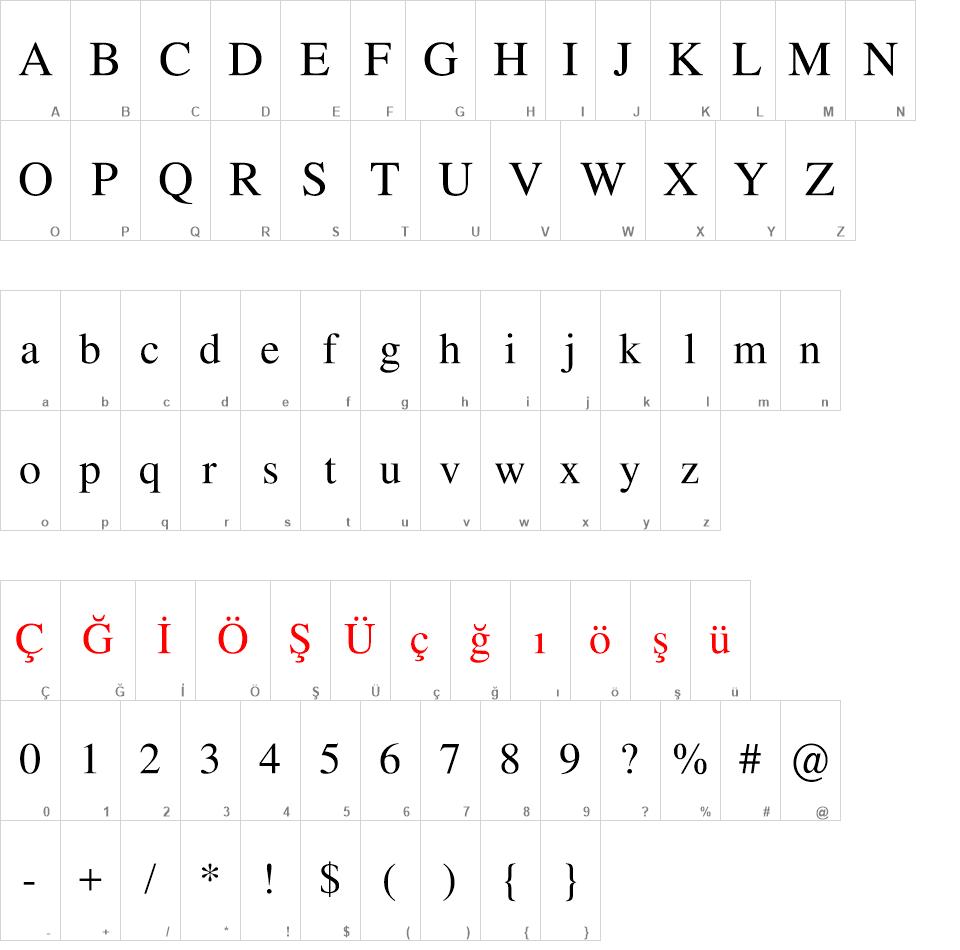
Nimbus Roman No9 L Font Family
Aus Wikipedia: Nimbus Roman ist eine Serifenschrift, die 1982 von URW Studio erstellt wurde.
Nimbus Novel No. 9 L wurde 1987 von URW Studio erstellt und 1996 schließlich von GPL und AFPL (Type 1 für Ghostscript) und Serifen in der LPPL veröffentlicht. Normal, Fett, Kursiv und Dunkel sind kursiv und sind frei lizenzierte Schriftarten, die von URW ++ angeboten werden.
Obwohl die Zeichen nicht genau gleich sind, hat der Nimbus Roman No. 9 L fast die gleichen Kriterien wie Times und Times New Roman. Eine der Ghostscript-Schriftarten ist eine kostenlose Alternative zu 35 grundlegenden PostScript-Schriftarten (einschließlich Times).
Viele Linux-Distributionen befinden sich in einem Standardartikel. In einigen Linux-Distributionen wurde OpenOffice.org als Standardschriftart in Writer verwendet (z. B. Ubuntu-8.10-Version, und die Standardschriftart wurde seit Ubuntu 9.04 in Salvation Serif geändert).